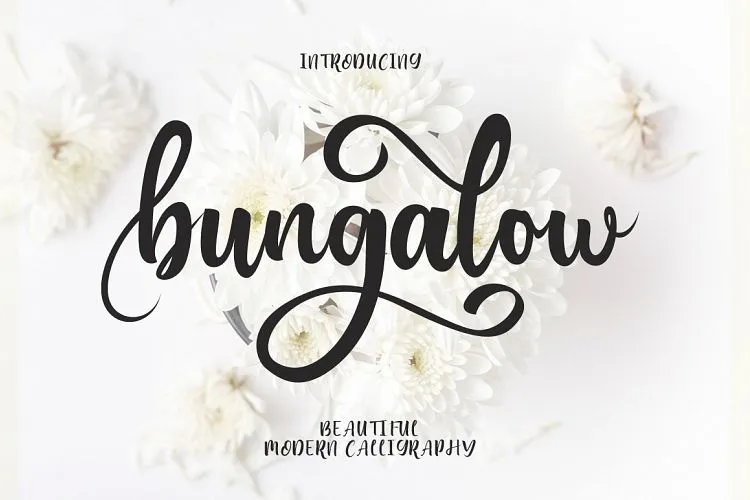
Bungalow Script Font – Download Grátis
Este é o novo Bold Script Calligraphy estilo tipográfico criado à mão pela designer 178-MC. A fonte traz uma aparência que se assemelha a letras de churrasco com um efeito retrô, apresentando traços elegantes e alternativas com desenhos suaves. O título ‘Bungalow Font’ nos lembra deste estilo moderno de letra churrasco. É uma fonte ideal para projetos diversos como cartões de aniversário ou anúncios de marca. Suporta idiomas internacionais, oferecendo alternativas estilizadas facílmente utilizáveis e instaláveis, garantindo que você tenha o melhor para cada projeto da sua empresa. Este é um recurso visual perfeito tanto para criar cartões de convite elegantes quanto para personalizar logotipos únicos.